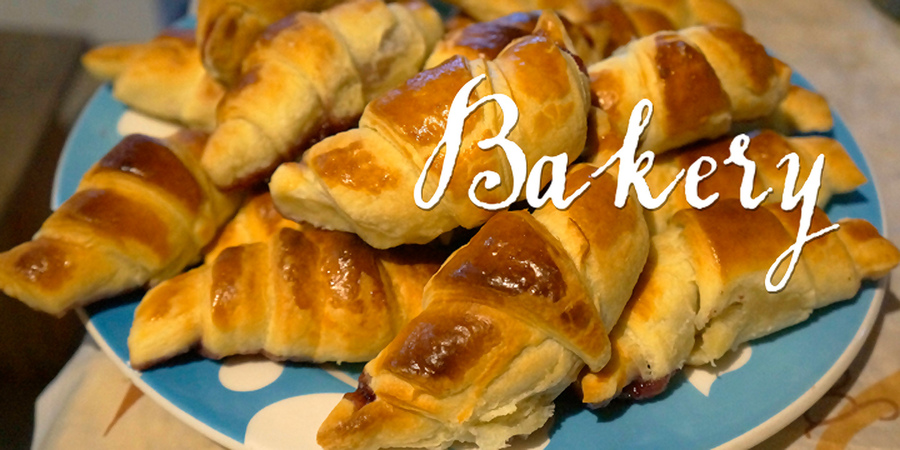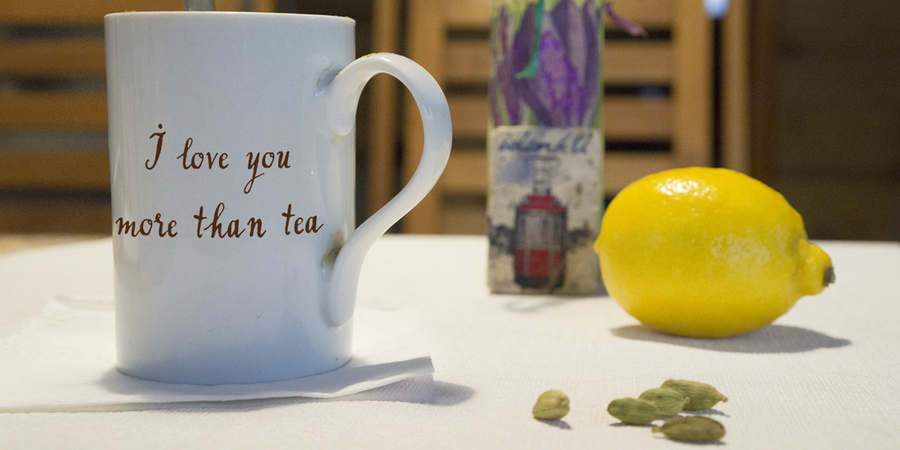
Bakery – це унікальне поєднання класичного та сучасного рукописного шрифту. Він був написаний каліграфічною ручкою. Bakery ідеально підходить для весільних урочистостей, заходів, запрошень, меню, логотипів, вітальних листівок тощо. Набір символів містить повний комплект латиниці та кирилиці. Шрифт розробила Марина Михальська за участю Сергія Ткаченко у 2017 році.
запрошення, афіша, лист, реклама, меню, обкладинка, журнал, плакат, монограма, анімація, мультфільм, листівка, привітання, етикетка, альбом, щоденник, пакування Адаптованість гарнітури до носіїв:
Асоціації з сімейством шрифтів BakeryОсобистість і характер гарнітури:
емоційний, чуттєвий, поетичний, оригінальний, характерний, грайливий, самобутній, мажорний, легковажний, вітряний, весняний, сентиментальний, кучерявий, артистичний, танцюючий, цікавий, декоративний, елегантний, епістолярний, натхненний, ліричний, динамічний, вільний, колоритний, живий, крафтовий, наївний, чарівний, милий, літній, свіжий, добрий, зелений, неформальний, веселий, непосидючий, неслухняний, пустотливий, рухливий, задерикуватий, ностальгічний, енергійний, привітний, мультяшний, смачний, рукотворний, натуральний, доброзичливий, добродушний, вигадливий, химерний, домашній, органічний, святковий, ввічливий, красивий, музичний, манірний, жіночний, художній, ошатний, романтичний, радісний, дівчачий, казковий, новорічний, старовинний, щасливий, теплий, приємний, ламповий, ремісничий, фермерський, творчий, осінній, гарненький, симпатичний, жіночий, артізанальний, рослинний, різдвяний, лісовий
розваги, завивка, брошка, біжутерія, аксесуари, хенд мейд, сад, клумба, щоденник, цукерки, гра, театр, подарунки, магія, Чарівна казка, кондитер, музика, вірші, чай, кава, весна, літо, дитяча книжка, пригоди, анімація, відпочинок, мультфільм, день народження, виставка, ресторан, татуювання, тату, прикраса, квіти, десерт, кафе, торт, свято, кондитерська, солодощі, казка, принцеса, різдво, Новий рік, антикваріат, булочна, пекарня, кохання, романтика, сукня, одяг, інтер'єр, кухня, ферма, торгівля, осінь, Хюґе, море, Інстаграм, графіка, ілюстрація, дім Гарнітура має ознаки стилів: